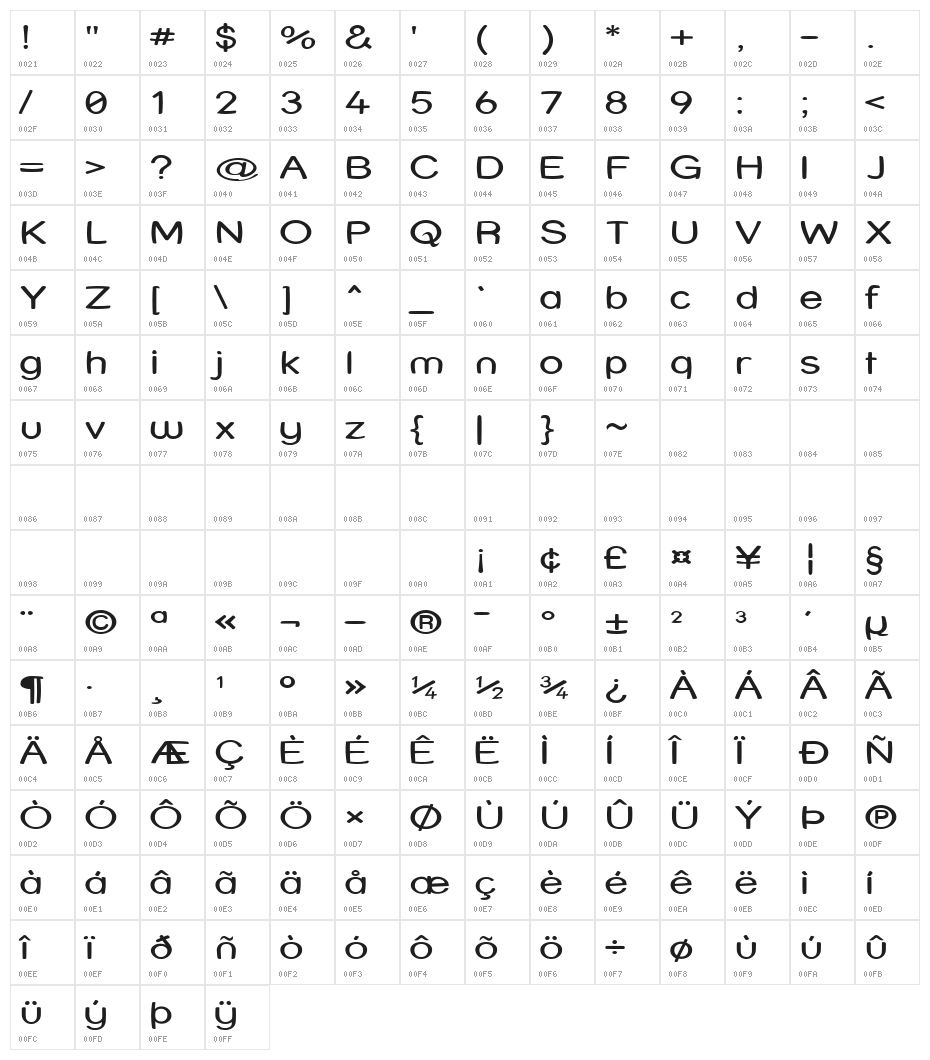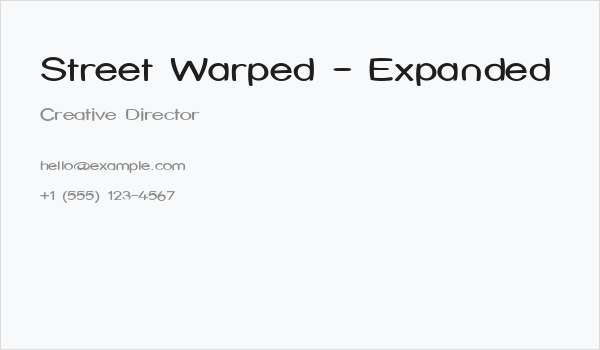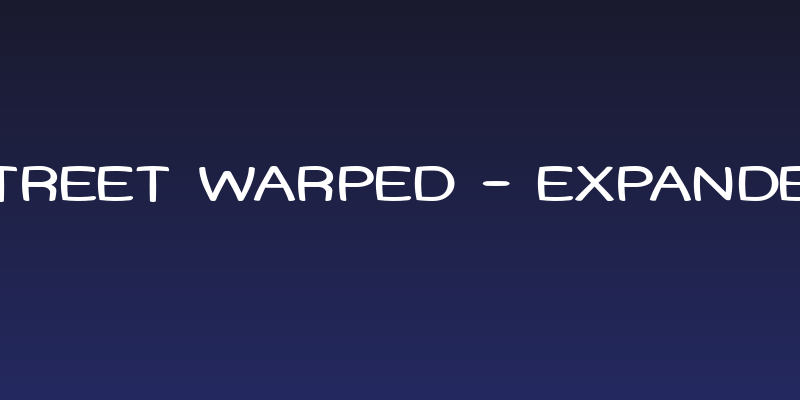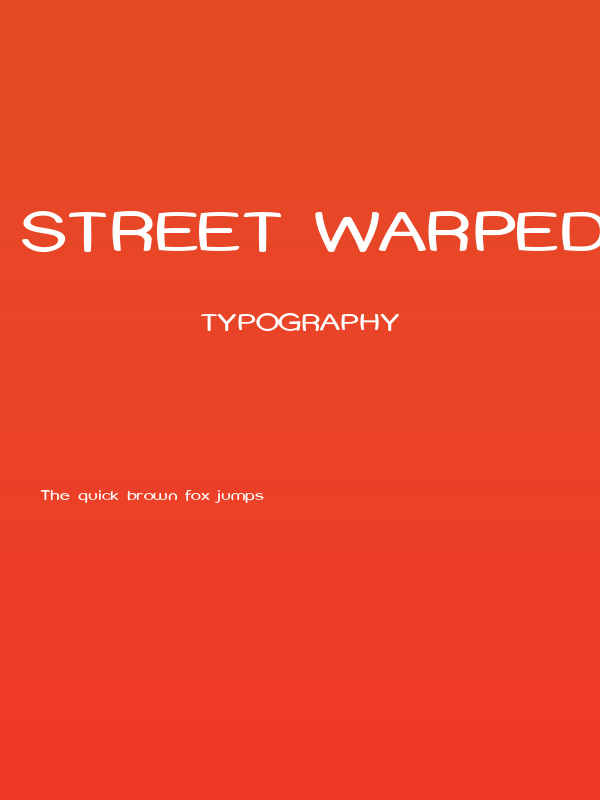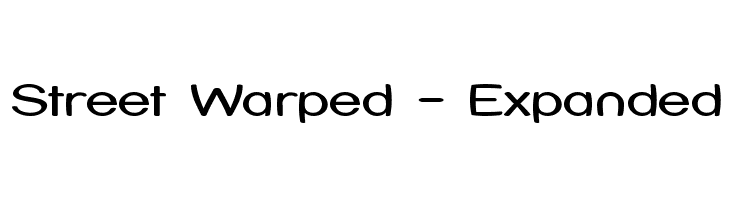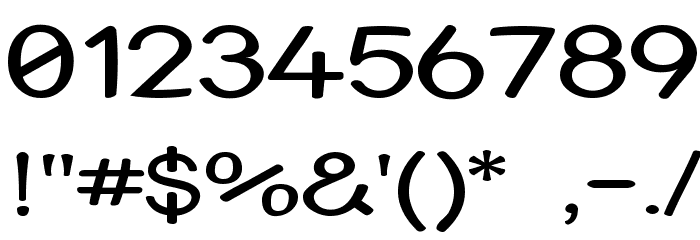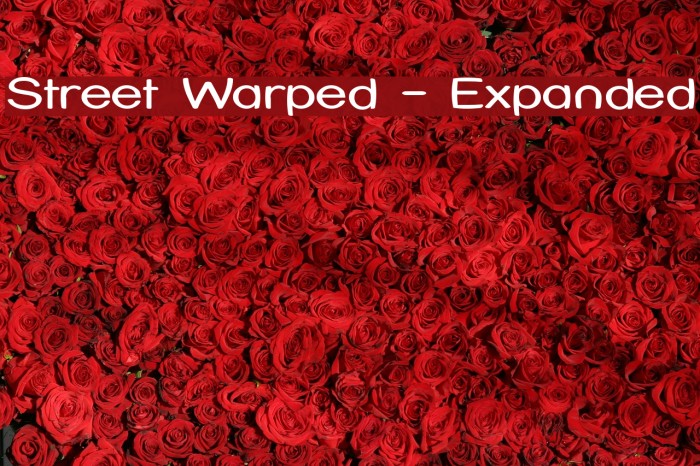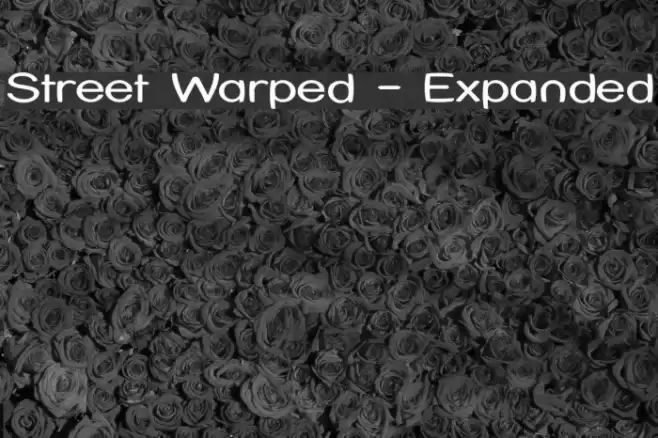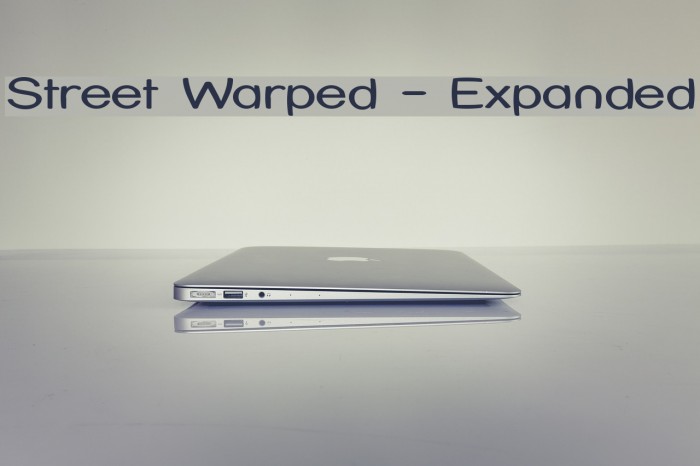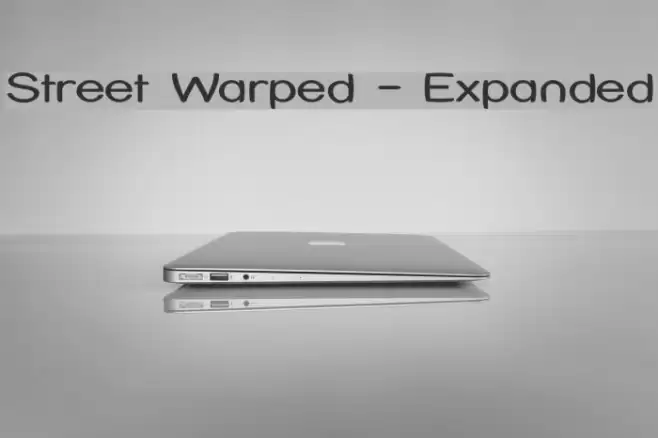
Street Warped - Expanded Font
| Largeur | Expanded |
| Style général | Playful |
| Projets proposés | Ideal for children's books, playful branding, casual invitations, and creative posters. |